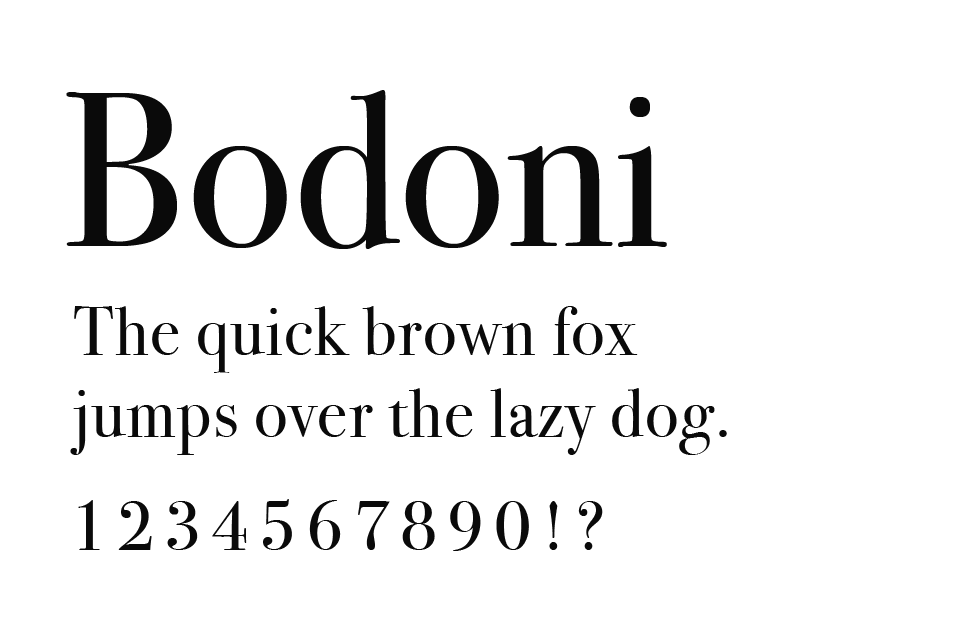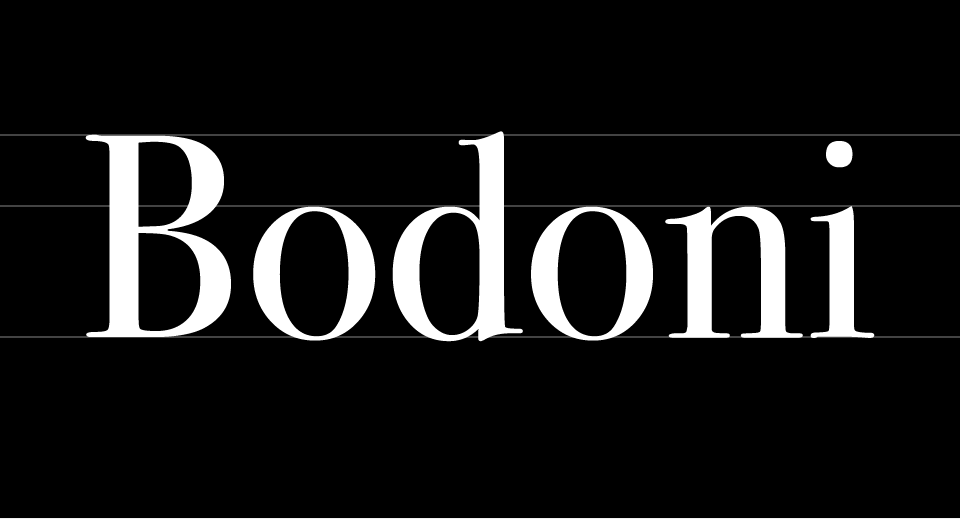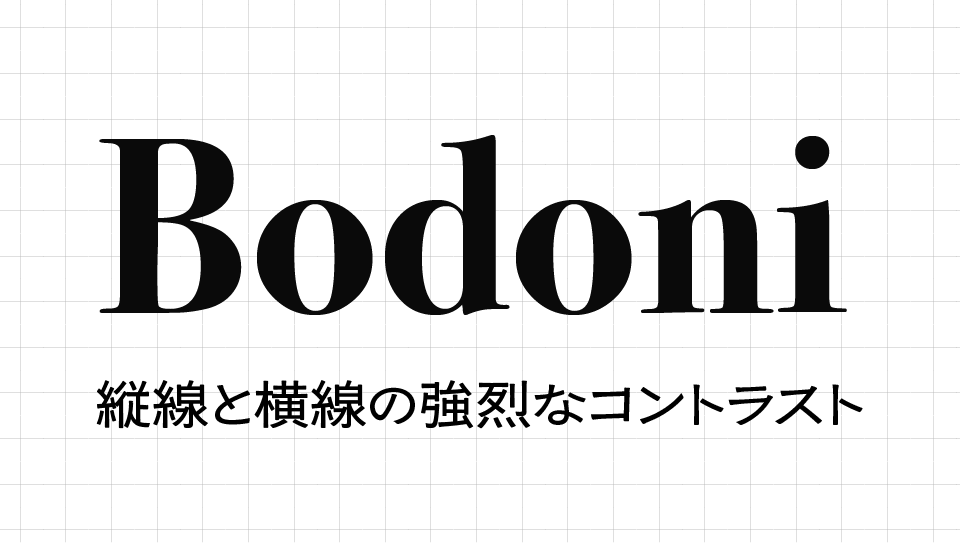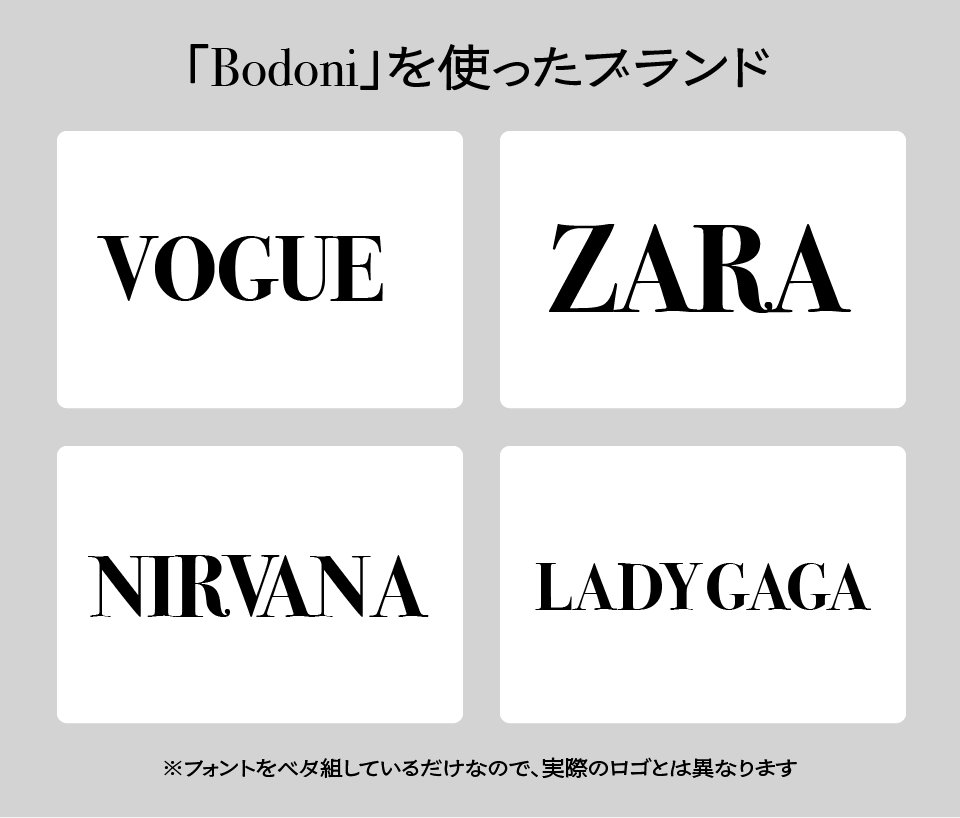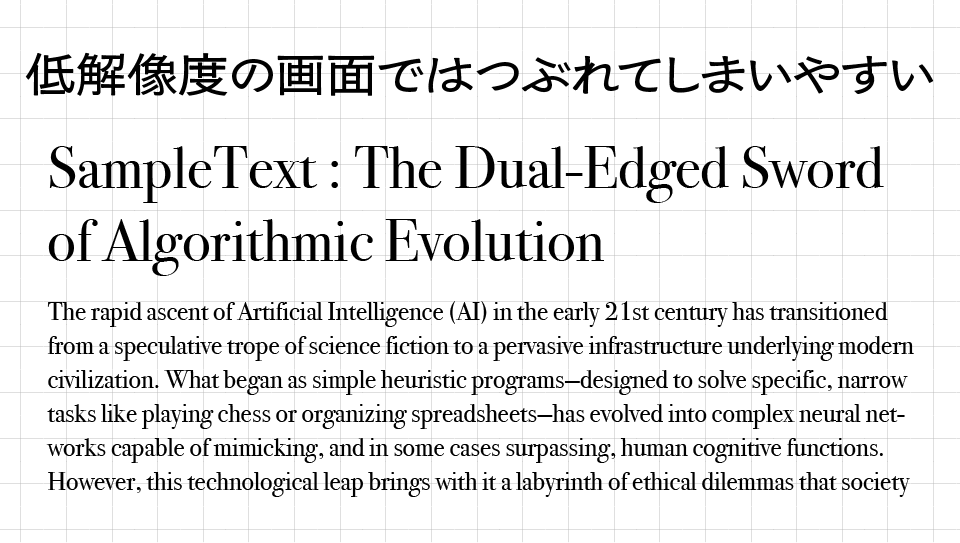
Bodoni(ボドーニ)フォントの魅力とは?クラシックとモダンを融合した書体
鋭く、美しく、そして華やか。そんな言葉が自然と浮かぶフォントが「Bodoni(ボドーニ/ボドニ)」です。18世紀に誕生したこの書体は、クラシックでありながら現代的な印象もあわせ持ち、ラグジュアリーブランドのロゴや雑誌のタイトル、ポスター、ファッション広告などで多く使用されてきました。
その最大の特徴は、繊細なヘアラインと力強い縦線のコントラスト。この極端なコントラストが生み出すリズムと緊張感は、他のどのフォントにもない独特の存在感を放ちます。この記事では、Bodoniの歴史やデザイン的特徴、代替フォント、代表的な使用例を通して、その魅力を深く掘り下げていきます。
Bodoni(ボドーニ/ボドニ)とは
Bodoniは、18世紀末にイタリアの印刷職人ジャンバッティスタ・ボドーニ(Giambattista Bodoni)によって設計されたセリフ体フォントです。当時、活版印刷の技術が向上したことで、より精密でシャープな書体の開発が可能になり、ボドーニは「モダン・ローマン」と呼ばれるスタイルを確立しました。
彼の目指したのは、無駄な装飾を排除し、洗練された対比と幾何学的な美しさで魅せる書体。その結果生まれたのが、太い縦線と極細の横線を組み合わせた大胆なコントラストを持つ、いわゆる“モダンセリフ”の代表格としてのBodoniでした。
Bodoniの歴史と背景
ジャンバッティスタ・ボドーニは、18世紀後半のイタリア・パルマで宮廷印刷所を任され、そこで自身の美学を徹底的に追求した書体設計に取り組みました。彼の目指したものは、ルネサンス期の古典的ローマン体(Garamondなど)とは異なる、「時代の空気を反映した新しい美しさ」でした。
その設計思想は、同時代のイギリス人タイプデザイナージョン・バスカヴィルや、フランスのディド家(Didot)からの影響も色濃く受けています。ボドーニ自身が出版した『Manuale Tipografico(タイポグラフィの手引書)』は、フォント史において重要な資料であり、彼の哲学と美意識が詰め込まれた遺産でもあります。
Bodoniの特徴
Bodoniの最大の特徴は、縦線と横線の強烈なコントラストにあります。
文字の垂直方向のストロークは極端に太く、水平の線やセリフ(文字端の飾り)はとても細く仕上げられています。この大胆な太さの差が、画面や紙面上で強い視覚的インパクトを生み出し、エレガントかつスタイリッシュな印象を与えます。
また、文字全体のシルエットは非常に幾何学的で、直線的な縦線ときれいにカーブする横線のバランスが絶妙です。字面は整然としており、理知的でクラシカル。それでいてシャープで現代的な印象も併せ持つのが、Bodoniの持つ美しさです。ただし、このコントラストの強さは小さなサイズではつぶれてしまうこともあるため、見出しやロゴといった「目立たせたい用途」に特化したフォントとも言えるでしょう。
類似・代替フォント
Bodoniはその独特なコントラストゆえに代替が難しい書体ではありますが、印象や構造が似たフォントもいくつか存在します。
代表的なのがDidot。フランス発の同時代モダンセリフ体で、Bodoniとよく比較される書体です。Didotのほうがやや装飾的で洗練された印象を与える一方、Bodoniはより直線的で構築的な雰囲気があります。
無料の代替としては、Libre Bodoni(Google Fonts)やModern No. 20などが挙げられます。Libre Bodoniはウェブフォントとしても扱いやすく、Bodoni特有の雰囲気を保ちながら、画面表示にも配慮された設計になっています。
Bodoniが使われている代表的な事例
Bodoniは、その高貴さとインパクトのあるデザインから、ファッション、アート、出版、ブランディングの世界で数多く採用されてきました。
ファッション誌『VOGUE』のロゴに使われているのはBodoni系のフォントであり、ラグジュアリーブランドの広告やポスターにも度々登場します。また、ファッションブランドZARAの旧ロゴでも、Bodoniに似た書体が使用されていました。
さらに、結婚式の招待状やシネマのポスター、高級商品のパッケージなど、「品格を出したい」「クラシカルな雰囲気を演出したい」という場面において、Bodoniは他に替えがたい存在感を発揮します。
Bodoniを使うときの注意点
Bodoniは視覚的にとても美しいフォントですが、その美しさはサイズや媒体に大きく左右されます。特に細いヘアラインは、低解像度の画面ではつぶれてしまいやすく、小さなサイズでは可読性が低下するリスクがあります。したがって、見出し・タイトル・ロゴなど、サイズが大きく取れる用途で使うのがベストです。
また、文字のリズムが硬質でやや装飾的なため、カジュアルなコンテンツや軽やかな雰囲気を出したい場面では重すぎる印象を与えることもあります。使い方次第で、上品さと堅苦しさの境界が変わる繊細なフォントとも言えるでしょう。
Bodoniは、気品と緊張感をまとう“静かな主役”のようなフォント
Bodoniは、大声で何かを主張するフォントではありません。しかし、その場にあるだけで空気が引き締まり、目を引き、そこに「品位」や「格」を持ち込んでくれるような力があります。そのコントラストの美しさは、まるで光と影のバランスを緻密に計算した建築のよう。整然としていながら、どこか詩的で、心に残る佇まいです。
「きれい」「クラシカル」「洗練」といった印象をフォントで表現したいなら、Bodoniはまさにその理想像です。ロゴや見出しに一文字置くだけで、その場が引き締まる。そんな“静かなる主役”として、Bodoniは今も多くのクリエイターに選ばれ続けています。